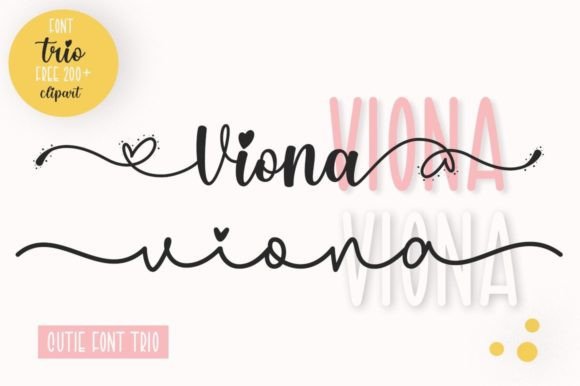
Viona
Doğru tasarım öğelerini bulmak zor olabilir, ancak Viona, çalışmanızı anında bir üst seviyeye taşıyan olağanüstü bir koleksiyon sunar.
İster İsteğe Bağlı Baskı (POD) ürünleri, ister düğün davetiyeleri veya sosyal medya grafikleri oluşturuyor olun, Viona ideal bir uyumdur.